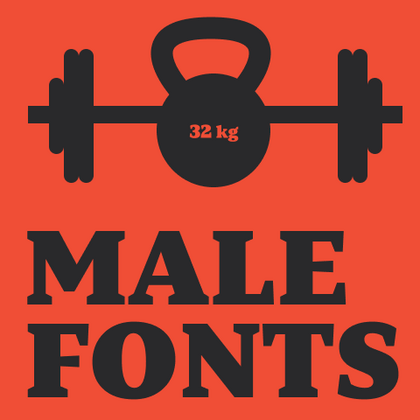
Maskuline Schriftarten
Für Projekte, die eine ausgeprägt kühne und maskuline Ästhetik erfordern, betonen maskuline Schriften Stärke und Raffinesse. Ihr Design balanciert Dichte mit eckigen Elementen und schafft eine beeindruckende Präsenz, während visuelle Harmonie erhalten bleibt. Im TypeType-Katalog finden Sie maskuline Schriften, die zu einer Vielzahl von Themen passen — von formellem Geschäftsbranding bis hin zu energiegeladenen Sportlogos. Ideal für Friseursalons, Männerkosmetik, die Automobilindustrie und mehr, verstärken diese maskulinen Schriften die Markenidentität mit einem Gefühl von Kraft und Selbstbewusstsein.
TT Neoris ist eine elegante Neo-Grotesk mit unbegrenztem Potenzial — eine Schrift, die alle modernen Anforderungen und Wünsche der Nutzer vereint.
TT Turns ist eine markante geometrische Sans Serif mit expressiven Elementen. Diese vielseitige Schrift eignet sich hervorragend für Fließtext und entwickelt in großen Schriftgraden einen ausgeprägten Display-Charakter.
TT Frantz ist eine experimentelle Variable Font, die sich durch ihre Schlankheit und Leichtigkeit auszeichnet. Die Variable beeinflusst die Höhe der Mittellinie: Durch Bewegen des Reglers lässt sich die Mittellinie der Schrift einfach anheben oder absenken.
TT Drugs ist eine serifenlose Schrift, die sich durch ihren starken Kontrast auszeichnet.
TT Biersal ist eine Display-Sans-Serif mit freigeistigem, verspieltem und abenteuerlustigem Charakter. Das Konzept dieser Schrift wurde von einem deutschen Plakat aus den frühen 1930er-Jahren inspiriert.
TT Paplane ist eine kantig wirkende Display-Sans-Serif.
TT Globs ist die erste Schrift aus der TypeType Starter Kit-Linie.
TT Carvist ist eigenwillig, verspielt und mutig — eine Schrift, die Aufmerksamkeit hervorragend auf sich zieht.
TT Espina ist eine Display-Antiqua mit ausdrucksstarken Serifen.
Wir haben eine brandneue Schrift veröffentlicht: TT Firs Text, eine geometrische Sans Serif mit nordischem Charakter.
TT Norms® Pro ist eine typografische Legende, die von weltbekannten Marken geschätzt wird. Entwickelt durch mehrere Iterationen, hat sie MyFonts erobert und typografische Vielseitigkeit neu definiert. Ein Design-Arbeitspferd, das sich von einem bescheidenen Werkzeug in einen unverzichtbaren kreativen Begleiter verwandelt.
TT Commons™ Pro ist das typografische Kraftpaket des Studios. Eine Schriftart, die so vielseitig ist, dass sie sich einer Kategorisierung entzieht und Stil und Funktion nahtlos verbindet. Für Designer, die eine universelle Grundlage suchen, die jedes Projekt aufwertet, ist dies die endgültige Wahl.
TT Hoves Pro ist eine skandinavische serifenlose Schrift, die minimalistische Eleganz versprüht. Sie ist die Geheimwaffe eines Designers, der komplexe Herausforderungen mit müheloser Präzision in visuelle Poesie umwandelt, und dabei gleichzeitig dezent und unverwechselbar.
TT Supermolot Neue verändert die visuelle Kommunikation grundlegend! Eine fortschrittliche, modulare serifenlose Schrift, die den Puls der technologischen Innovation einfängt und eine elektrisierende Vision für alles von immersiven Spieloberflächen bis hin zu kühnen visuellen Erzählungen bietet.
TT Firs Neue ist eine ausgewogene serifenlose Schrift, die von der skandinavischen Designphilosophie geprägt ist. Elegant und vielseitig, poliert durch zwei bewusste Überarbeitungen, um typografische Perfektion zu erreichen.
TT Rounds Neue ist eine weiche und freundliche Schrift, die es versteht, anders zu sein. In leichteren Schriftschnitten wirkt sie minimalistisch und neutral. In den fetten Schriftschnitten bläht sie sich auf und erreicht maximale Rundheit, die kindlichen Charme ausstrahlt.
TT Fors ist ein Schweizer Taschenmesser der Typografie. Diese geometrische serifenlose Schrift ist durch ihre klaren, raffinierten Proportionen vielseitig einsetzbar. Sie kann zur Definition von Schnittstellen oder zur Gestaltung von visuellen Akzenten verwendet werden.
TT Ramillas ist eine stilvolle und moderne Serifenschrift, die Design zu einer Kunstform erhebt. Sie zeichnet sich durch ihre einzigartigen dekorativen Stile und Initialen mit floralem Ornament aus und schafft visuelle Erlebnisse, die wirklich einmalig sind. Die mit dem Modern Cyrillic Award ausgezeichnete Schrift, die bereits über 3000 Websites weltweit ziert, definiert typografische Raffinesse neu.
Ausgangspunkt des Projekts TT Trailers war die Idee, eine neue Generation schmaler Schriften für den Einsatz in Filmabspännen und Plakaten zu entwickeln.
Bei der Gestaltung von TT Mussels haben wir großen Wert darauf gelegt, auch umfangreiche Textmengen komfortabel setzen zu können. Man kann sagen, dass TT Mussels zu den seltenen technologischen Textschriften gehört.